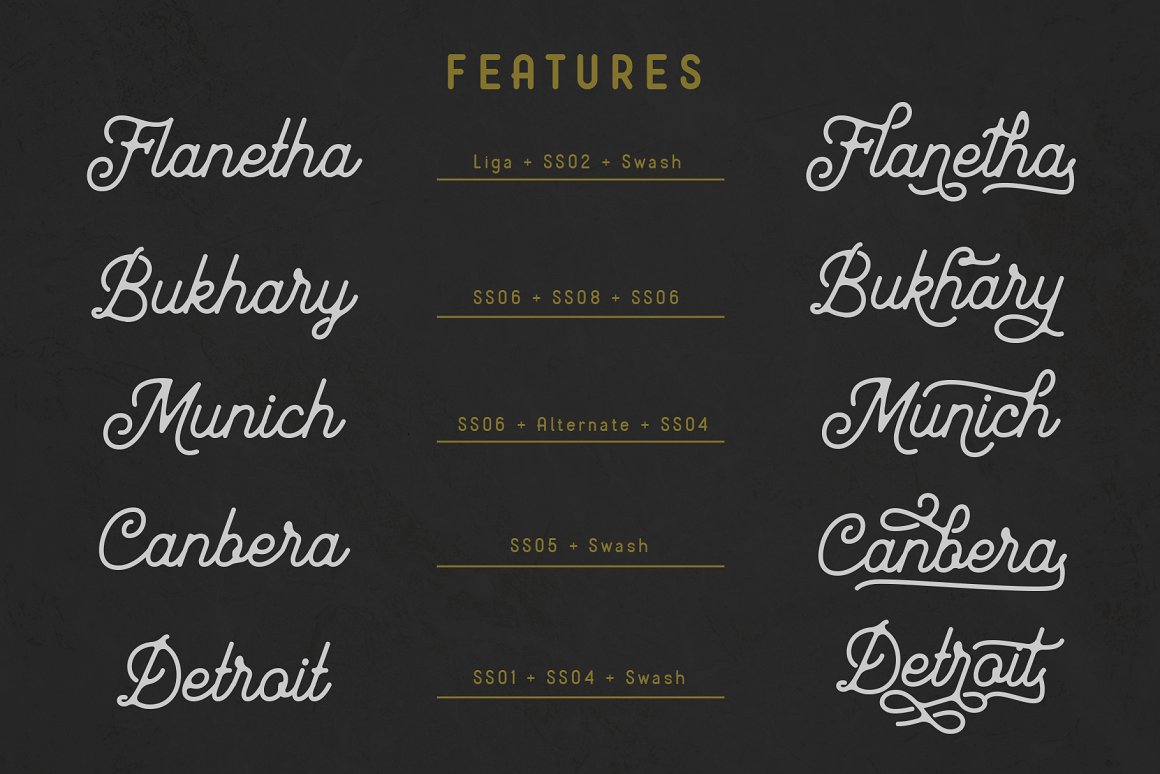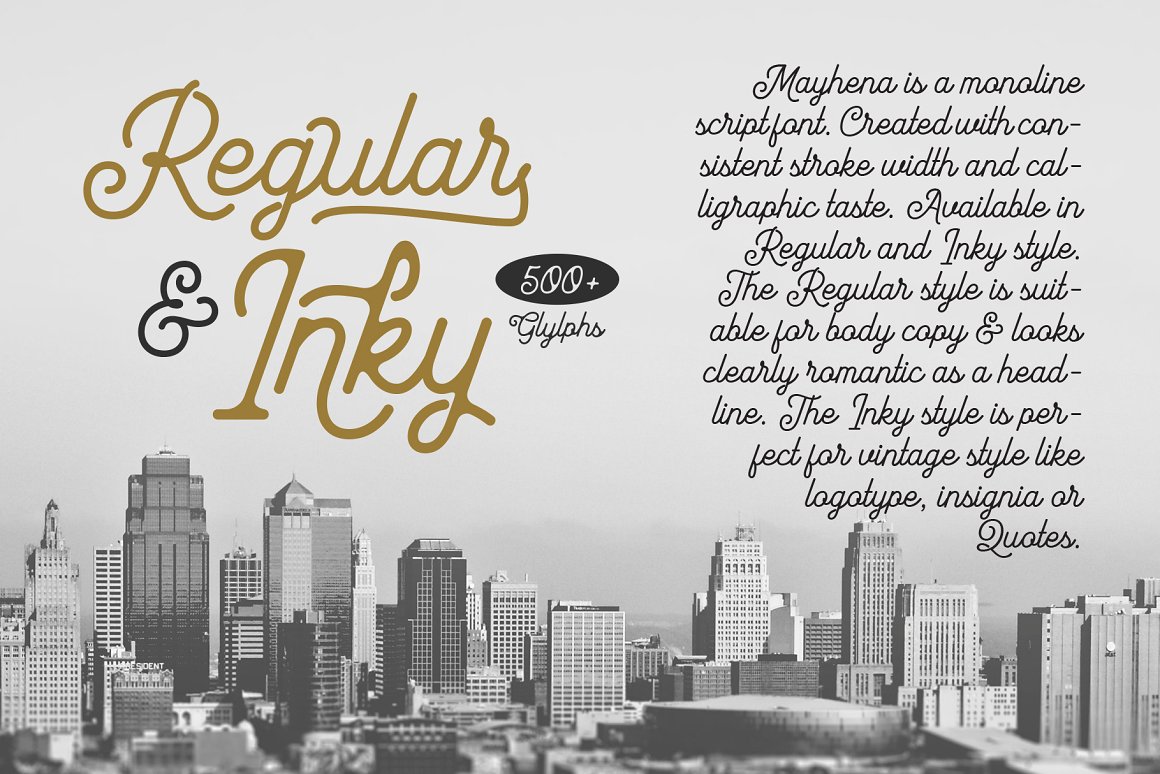
Font Mayhena Monoline Việt Hóa – Kiểu font cổ điển
Phông chữ Mayhena hoàn chỉnh với các kiểu thay thế và bộ từ 01 đến 08 mà bạn có thể thực hiện nhiều biến thể của kiểu chữ như swash dài, swash ngắn, đuôi trang trí, nét cuối và nhiều hơn nữa. Hỗ trợ 27 ngôn ngữ với hơn 500 glyphs!
• Uppercase
• Lowercase
• Symbols
• Numbers
• Accents
• Ligatures
Alternates
• SS01 – SS08